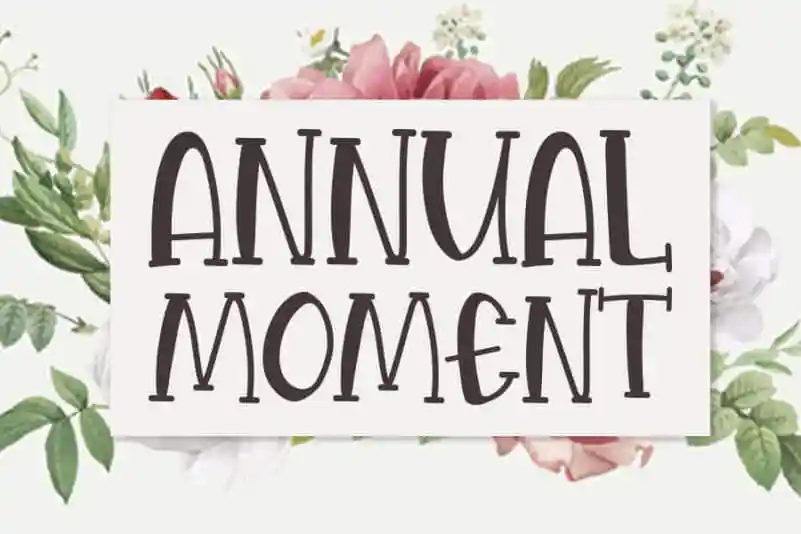
Annual Moment Display Font – Download Grátis
A fonte ‘Annual Moment Display Font’ foi criada com uma combinação impressionante de um can fio e uma lapiseira, resultando num visual extremamente encantador e autêntico. Esta fonta exuberante e única é ideal para transformar qualquer projeto DIY em algo digno de aplausos. A simplicidade da sua forma feita à mão realça o seu caráter único, tornando-a perfeita para aplicação em diversos estilos gráficos do design personalizado. Sua elegância criativa e moderna é perfeitamente adaptada para adicionar um toque especial a qualquer projeto de arte digital ou impressão. Não importa qual seja o seu objetivo – seja uma etiqueta de vinhos, um cartaz em evento social, ou até mesmo uma camiseta personalizada. A ‘Annual Moment Display Font’ é definitivamente a fonte perfeita para quebrar as regras e fazer algo realmente único.